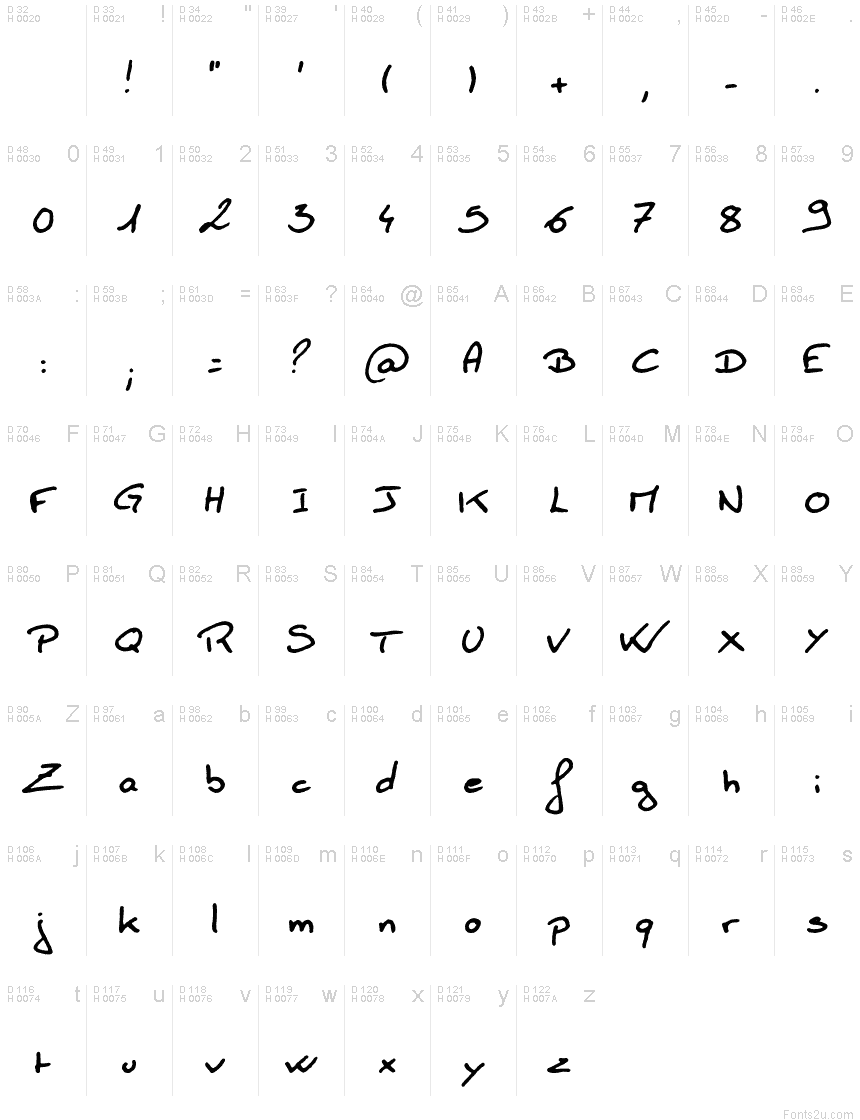
Boluge to darmowy krój pisma imitujący pismo odręczne, z luźnym charakterem pędzla i swobodnym rytmem. Litery balansują między szerokimi, zaokrąglonymi pętlami a szybkimi, dynamicznymi ruchami, co nadaje napisom osobisty, wręcz szkicowy ton, zamiast wygładzonego, kaligraficznego wykończenia.
Dzięki temu jest to naturalny wybór do zinów, menu kawiarnianych, opakowań handmade, plakatów czy projektów typu scrapbook, gdzie darmowy font pomaga zachować na stronie luźny, ludzki klimat. Sprawdzi się też świetnie w krótkich nagłówkach, na kartach tytułowych czy w szkicach logo, ponieważ duże, zapętlone formy i miękkie krzywizny budują charakter nawet przy niewielkiej liczbie znaków.
Stephane Deluce